フィットフォントサービスの紹介03「漢字・仮名・欧文の組み合わせ」
フィットフォントサービスでは、パートナーの欧文フォントとタイププロジェクトの日本語フォントを組み合わせて、ひとつのフォントとして提供することができます。
タイププロジェクトのサイトでは、漢字・仮名・欧文の様々な組み合わせをシミュレートすることができます。画面上のスライドバーでウエイト、コントラスト、字幅、フトコロを調整することで用途に合わせた最適な組み合わせを探すことができます。
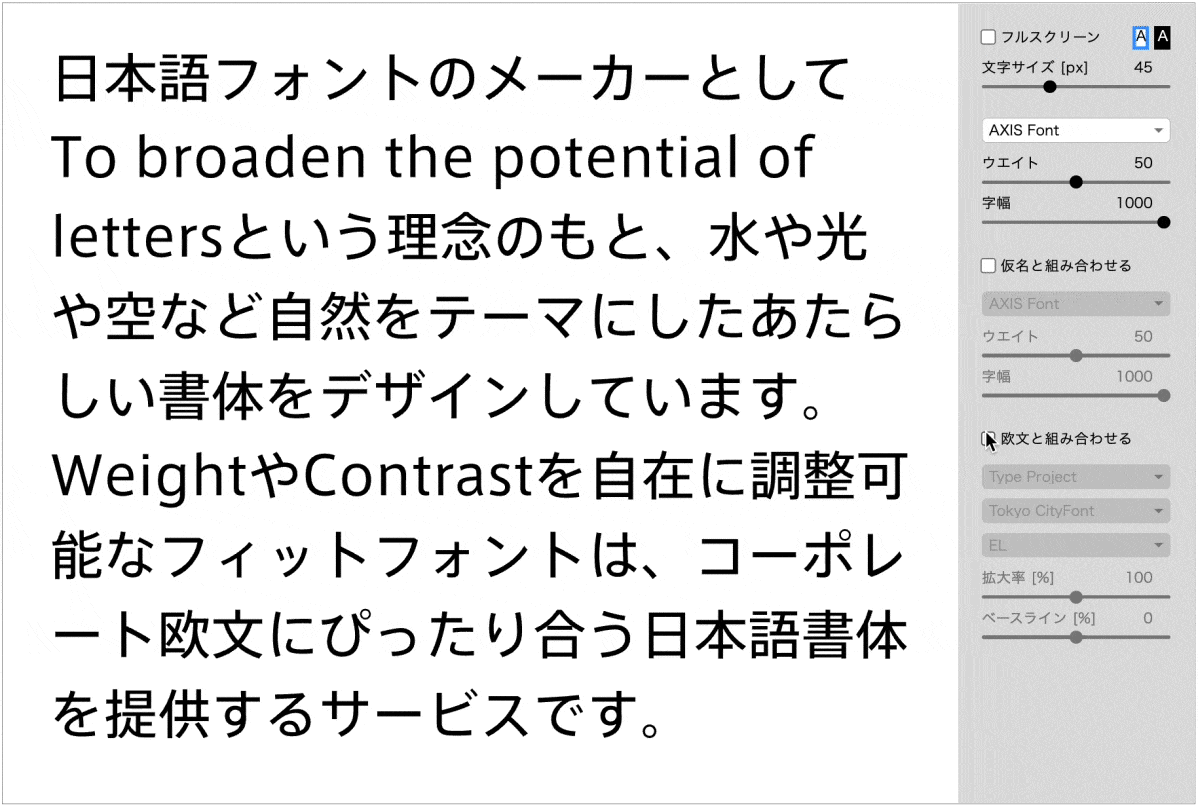
このシミュレーターでは、便宜上、AXIS FontとTP明朝のそれぞれが1071のバリエーション、 TPスカイでは、26段階のコントラストと34段階のウエイト、16段階の字幅、26段階のフトコロで数多くのバリエーションを用意しており、シームレスな生成が可能です。